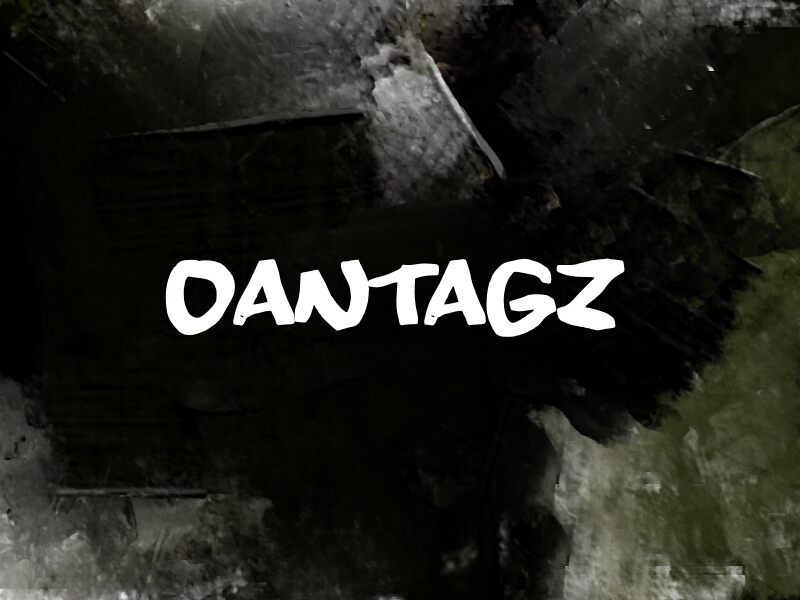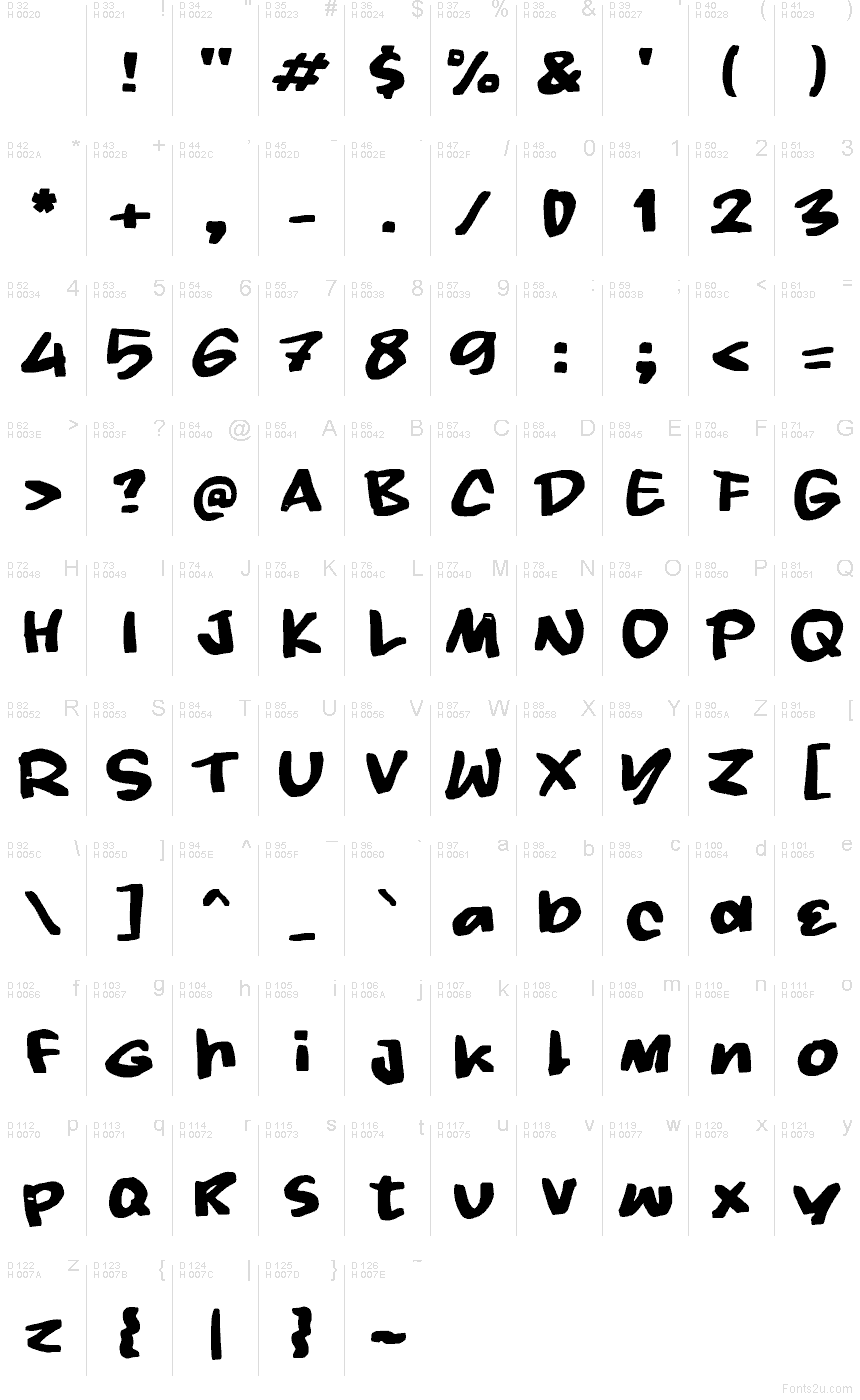
OANTAGZ od Wep je bezplatné brush písmo charakteristické širokými tahy štětcem, ráznými obraty a lehce nepravidelným ručním rytmem. Písmena působí dojmem, že byla namalována plným štětcem, nikoli vykreslena podle úhledné předlohy, což jim dodává syrový plakátový vzhled, který zůstává přímý a čitelný jako display písmo.
Tato surová malovaná textura dává smysl na hudebních letácích, streetwear grafice, skateboardovém brandingu, plakátech na akce a výrazných nadpisech na sociálních sítích, kde by uhlazená typografie působila příliš upjatě. Krátké texty na obalech a titulky také těží z jeho roztřepených okrajů a kompaktní malované hmoty, které velkým slovům dodávají rychlý, ručně vytvořený šmrnc.
Oantagz
Prezentace a vizuální ukázka písma OANTAGZ